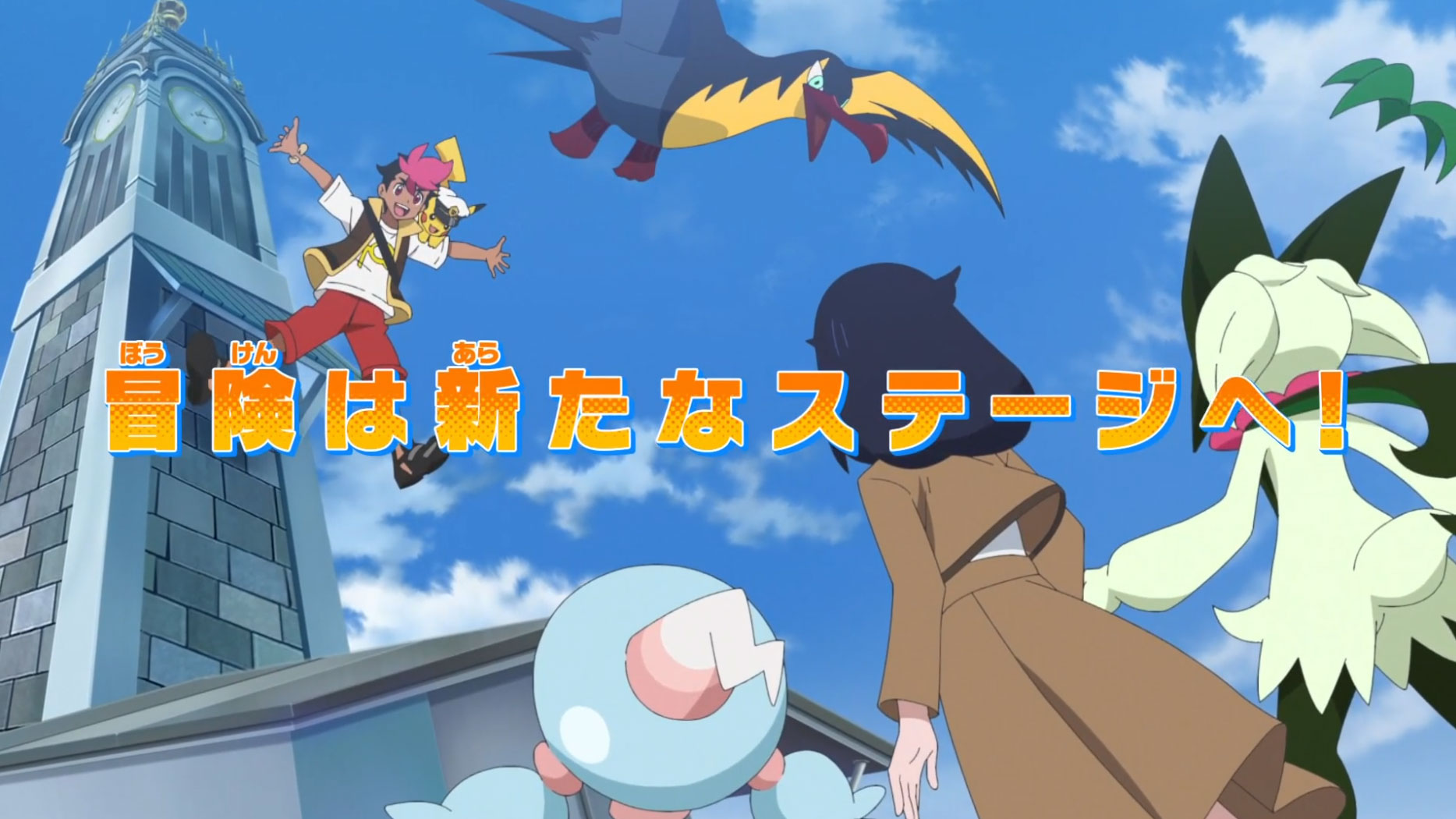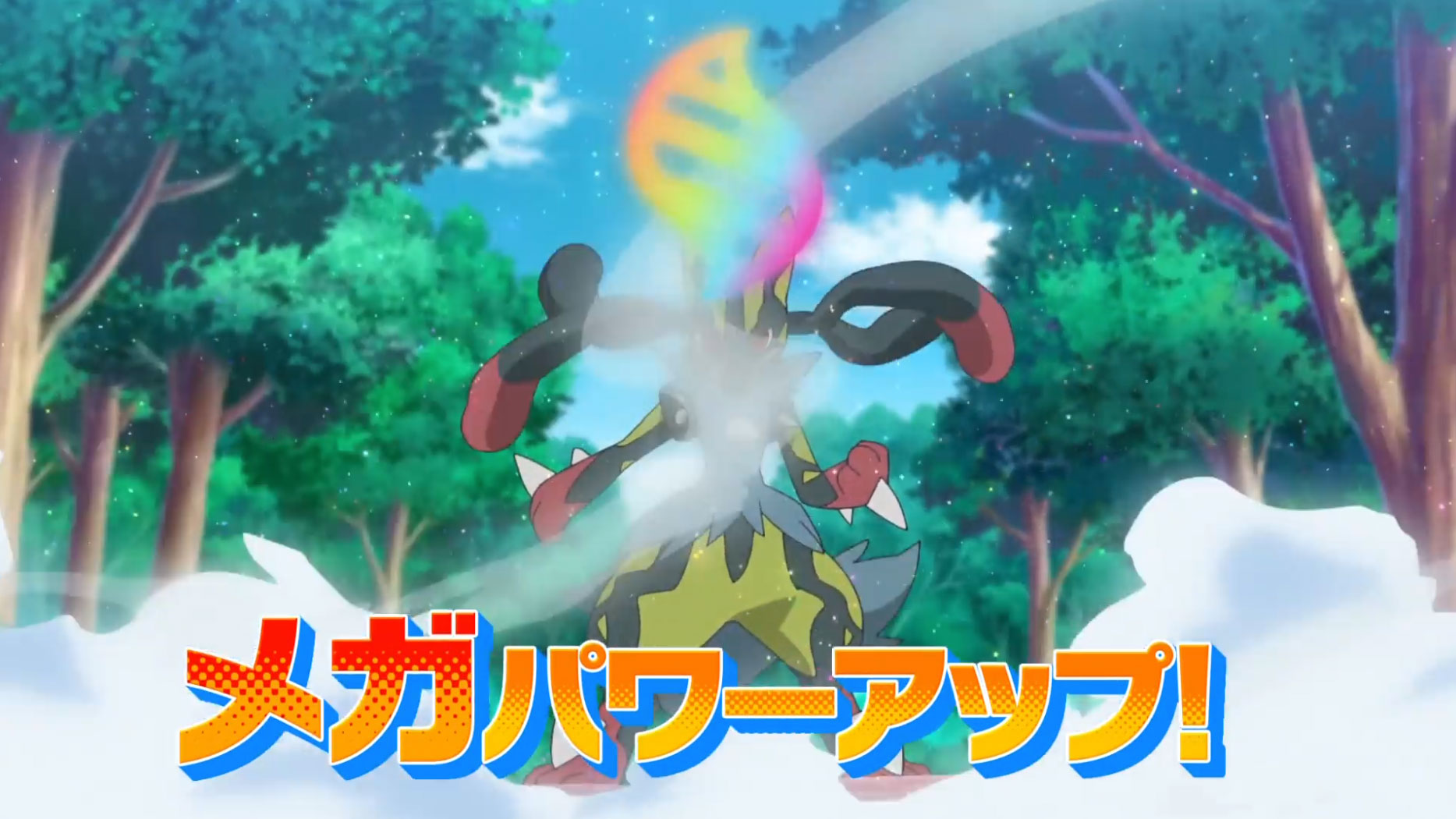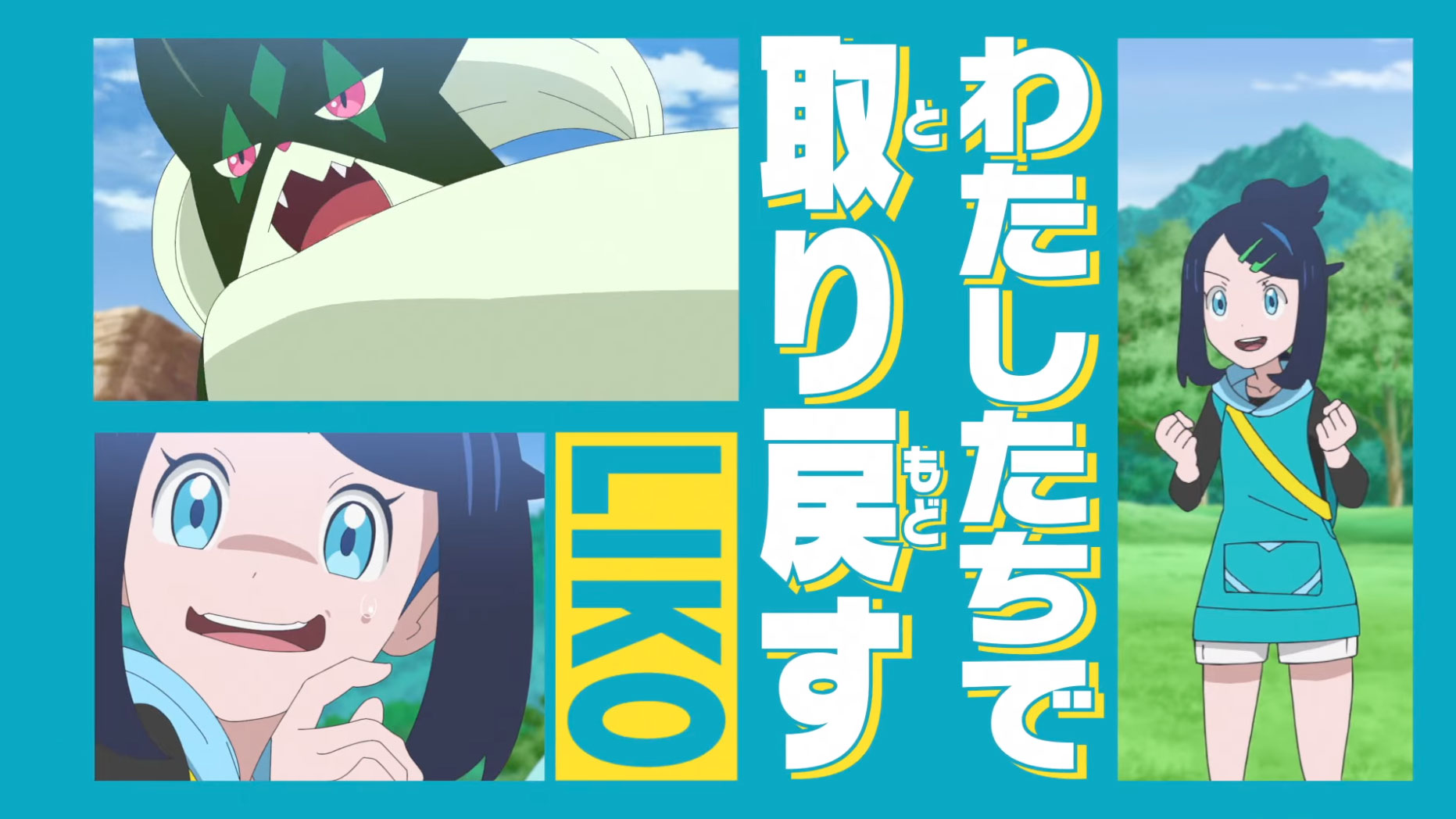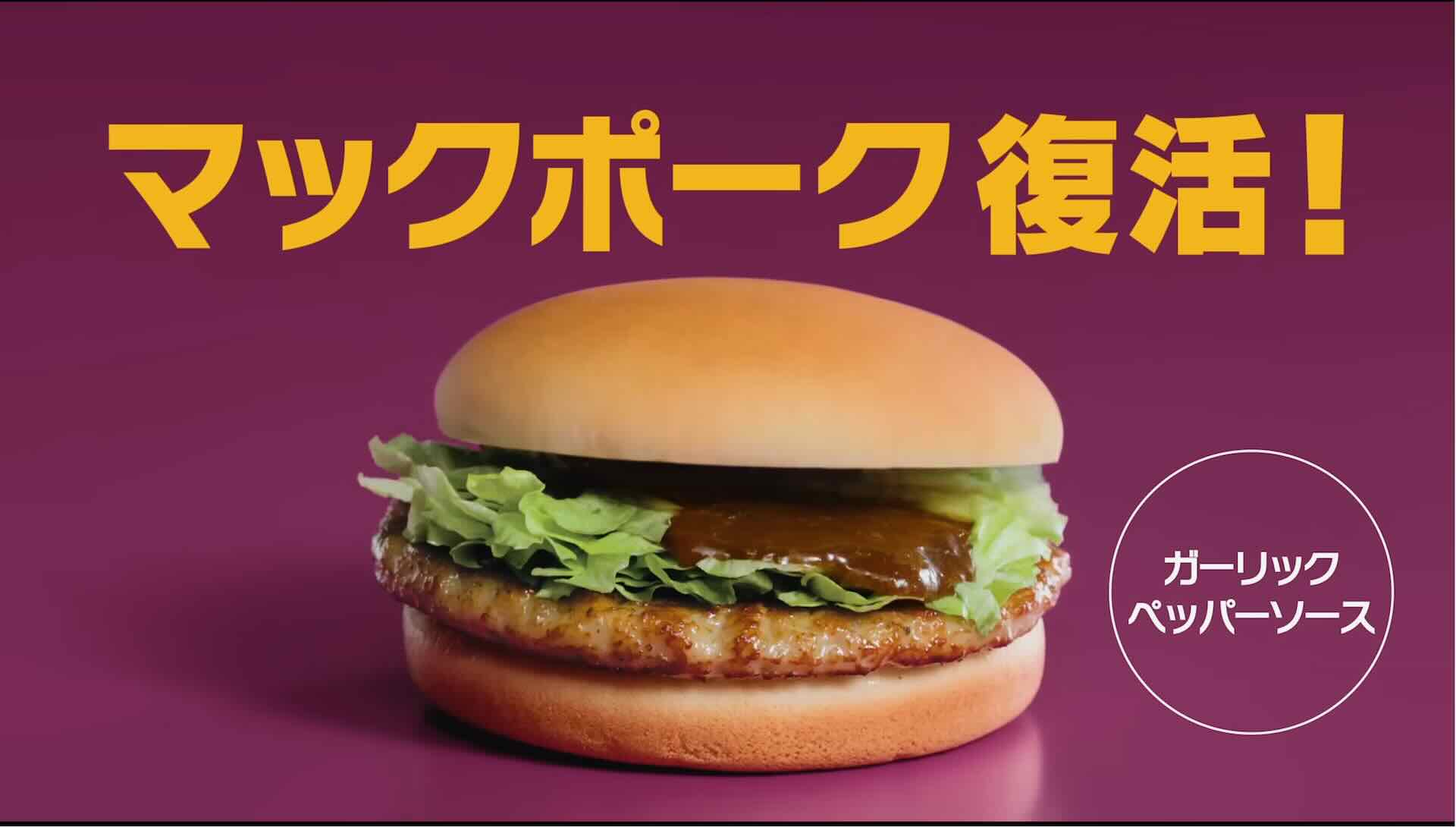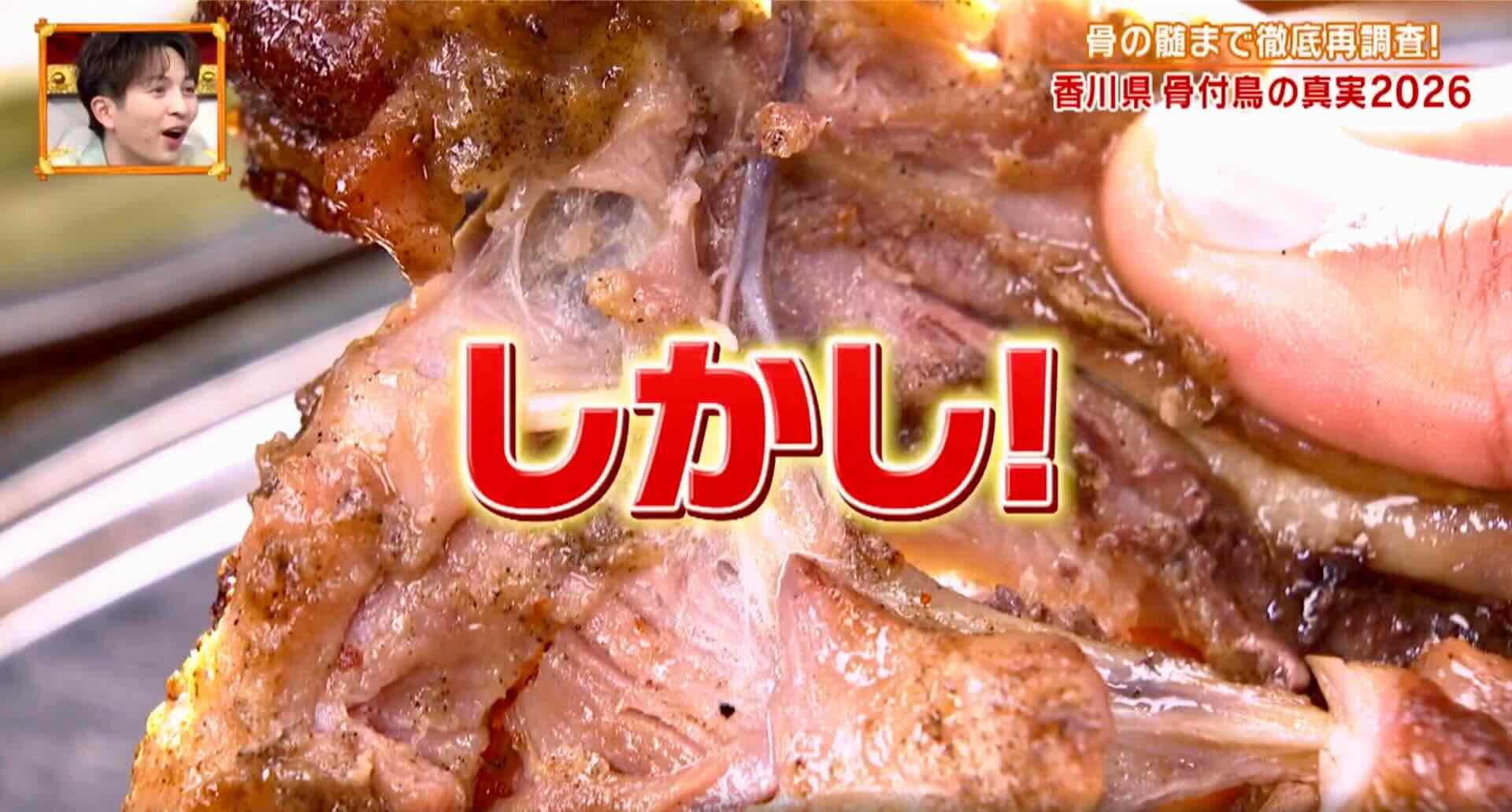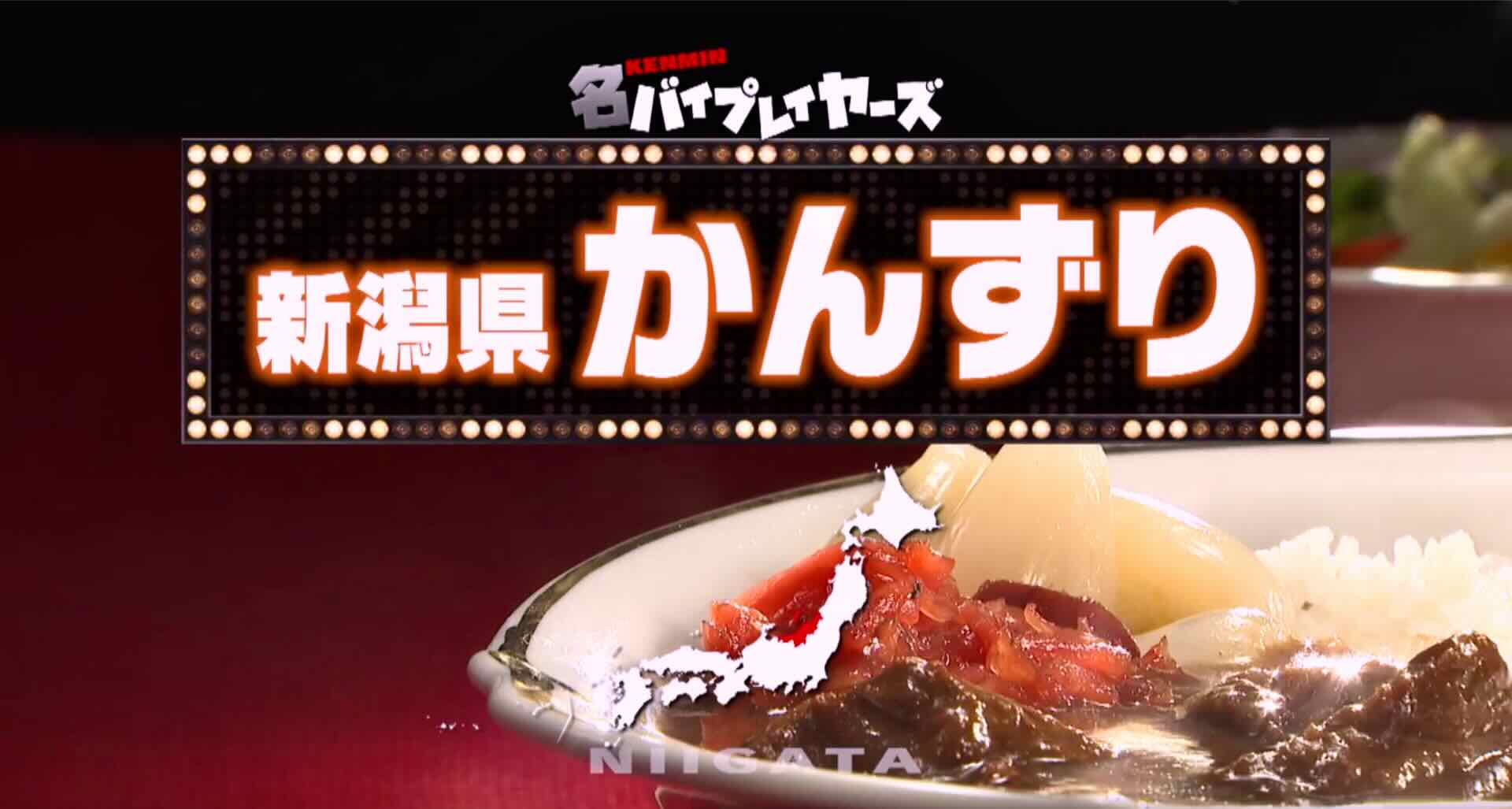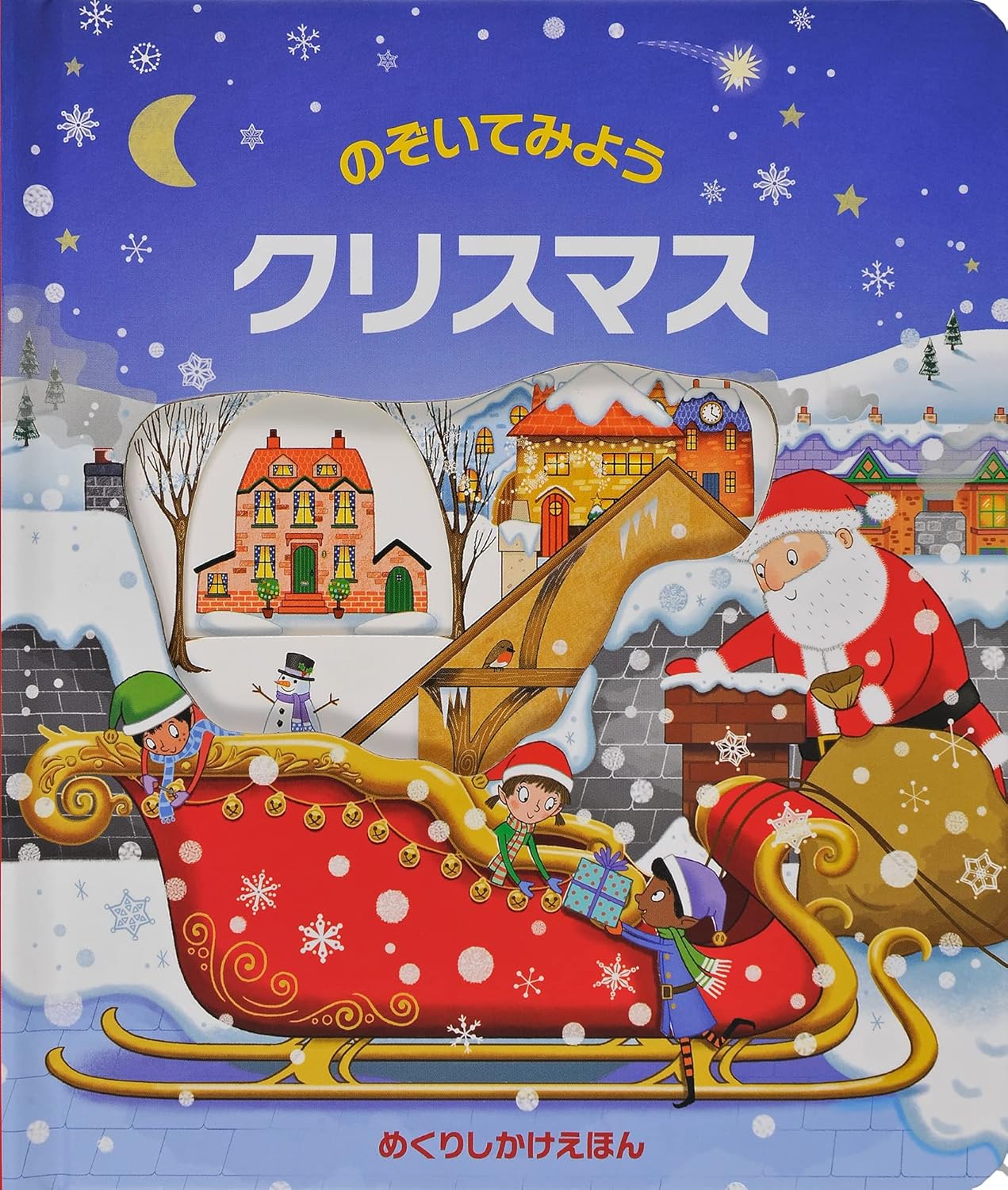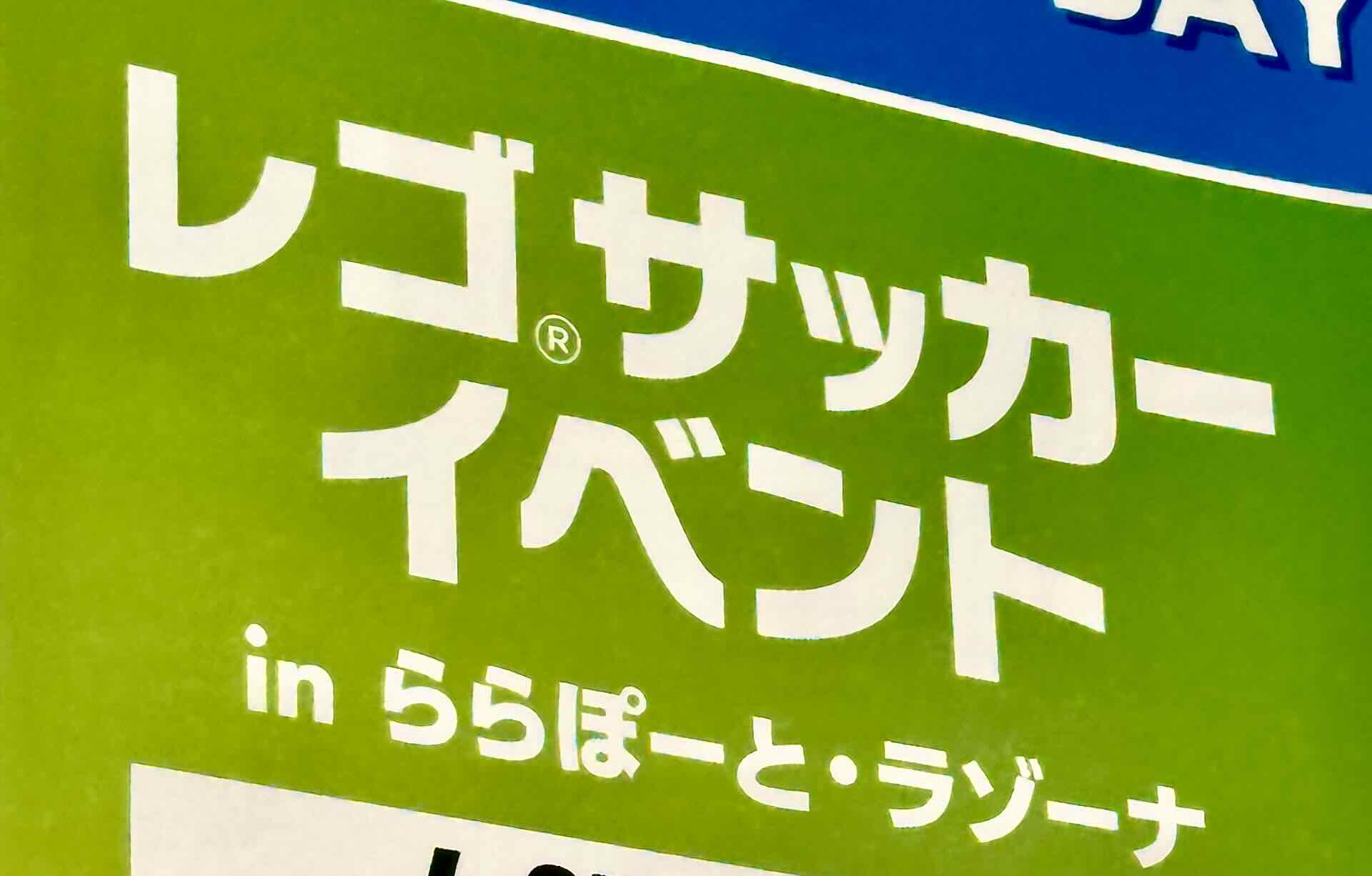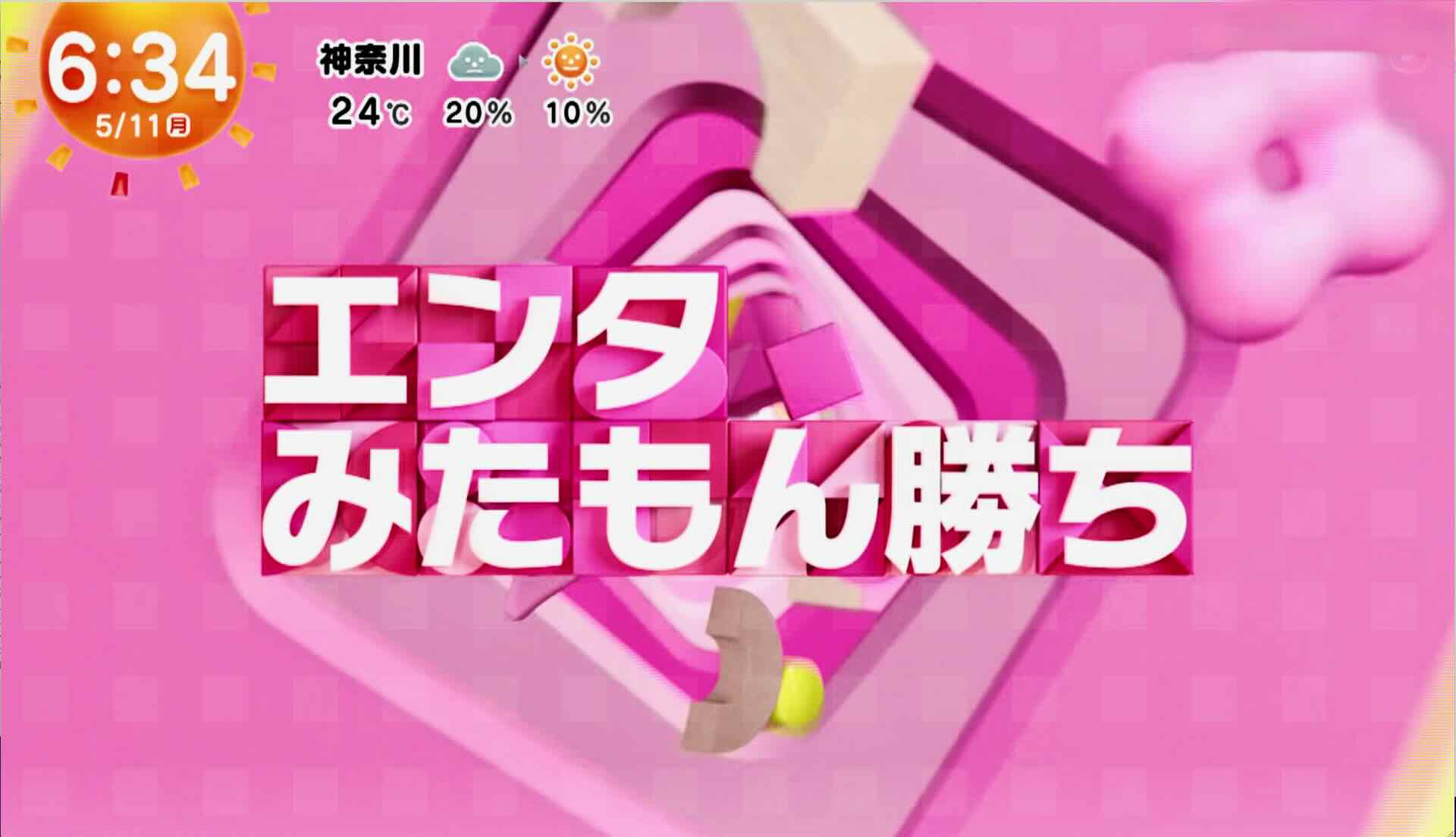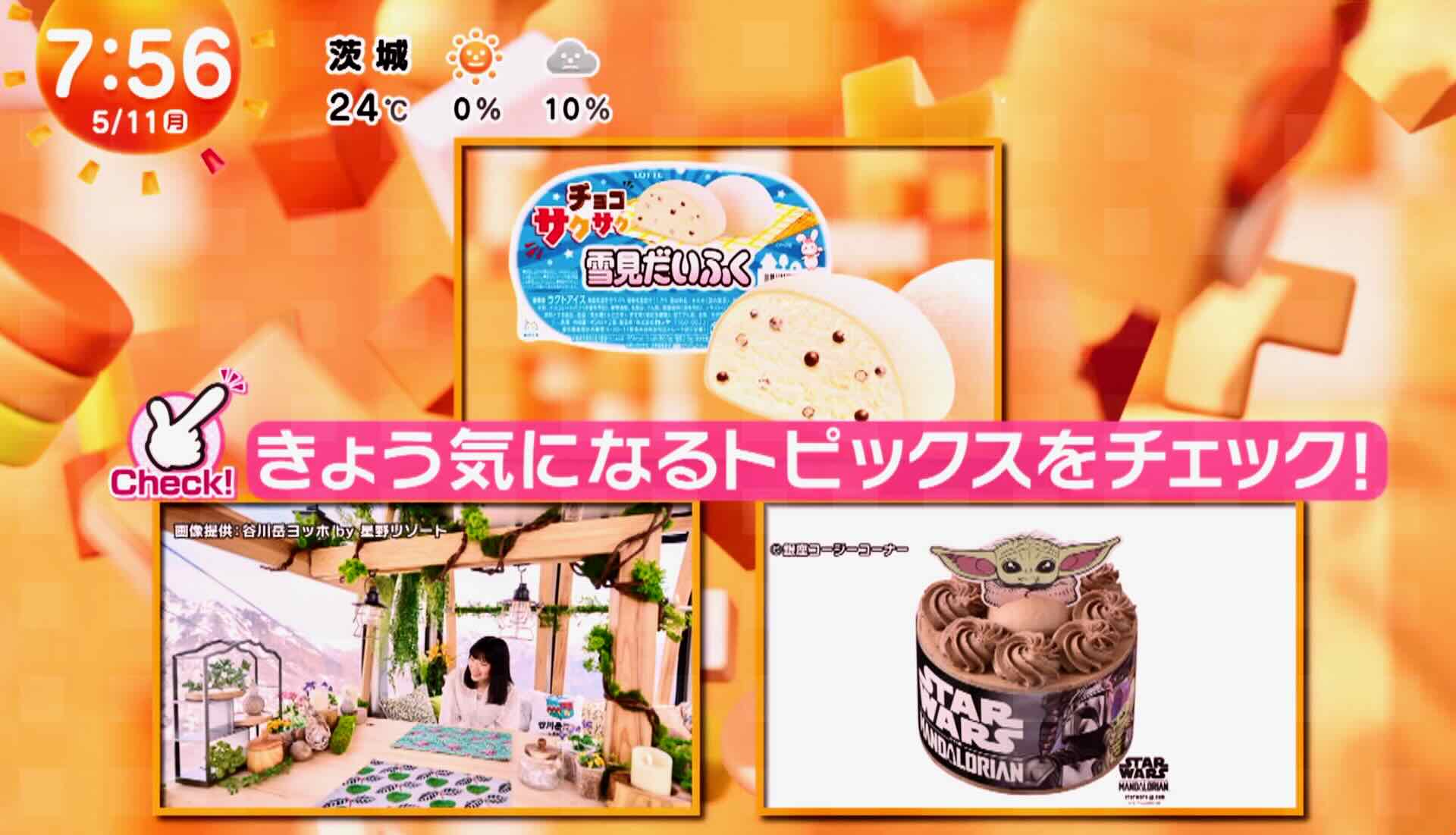
かな書体「ニタラゴ(ニュータイプラボゴシック)」は
フォントワークスでは「NTLG」、モリサワでは「タイプラボN」という名で
広く販売され、多くの人に使われています
そして一部のウェイトは、AdobeFontsでも使えます
神戸で出会った…。
全体はこんな感じ。
集合住宅の秋祭りで見た幟旗。
幟旗全体は、こんな感じ。
「星のカービィ」の公式Xアカウント  takumi  2026年10月3日(土) 13:20  HP
星のカービィの公式Xアカウントにアップされている画像でニタラゴ書体が使われています。
上の「プレゼントキーワードで〜」を除き、大部分がM社のニタラゴです。
もう1枚。
少し前までは、旧F社のニタラゴが使われていたようです。
旧F社とM社のニタラゴを判別するには、英数字を観察するしかありませんね…。
ゲームのセール告知画像  takumi  2026年9月27日(日) 19:58  HP
「冒険家エリオットの千年物語」というゲームのセール告知画像でニタラゴ書体とあられ書体の両方が使われています。
両書体の掲示板に同じ内容を投稿させていただきます。
画像は公式Xとスクエニ公式サイトの両方にアップされています。
特徴のある英数字を見ると、ニタラゴルイカのようですね。
小田急線車内の中吊り広告。
こんな感じ…。
マクドナルド、タルタルデミ。
これは、ポスター。
炭酸飲料「ギルティ炭酸 NOPE(ノープ)」
これも。
ANA国内線タイムセール
書名:トミカ超図鑑ハイパー
著者:(株)タカラトミー
発行:ポプラ社
書名:とりをよぼう
著者:作:大久保茂徳 監修 絵:ひやまゆみ
発行:ひさかたチャイルド